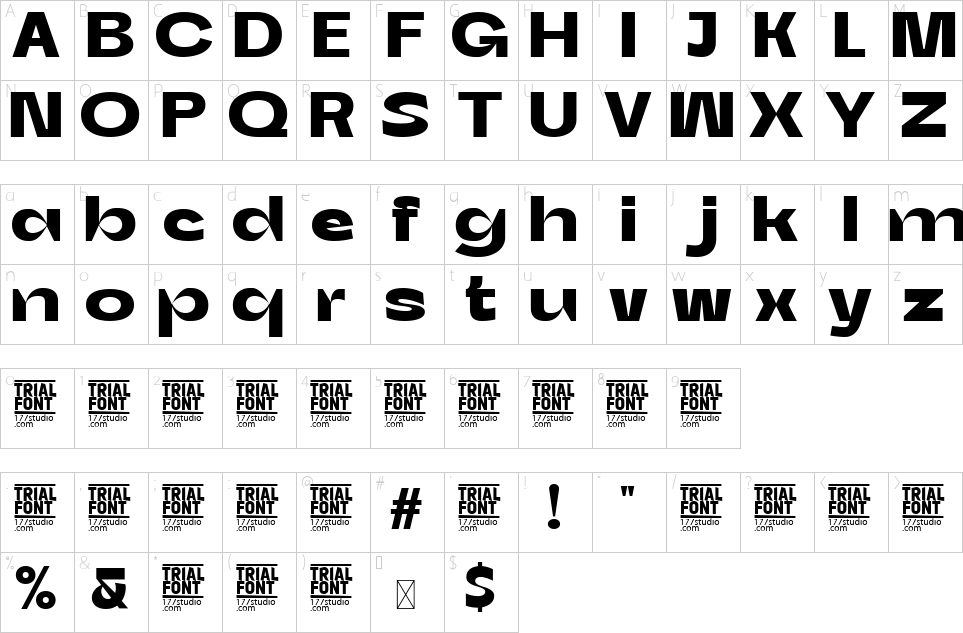
A fonte Salvador Abstract é uma escolha perfeita para designers que procuram um estilo minimalista e moderno. Essa fonte foi projetada pelo 177studio.com e tem um design abstrato que pode se destacar em qualquer projeto. Suas linhas levemente geométricas e cores neutras permitem que você personalize sua tipografia de forma única, criando um efeito visual rico e sofisticado. Download Salvador Abstract para Windows e Mac e experimente a nova tendência em fontes gratuitas. Esta é uma excelente maneira de adicionar um toque de originalidade a qualquer projeto gráfico. Com mais de 784 downloads, é claro que Salvador Abstract está ganhando destaque no mundo dos recursos gráficos gratuitos.